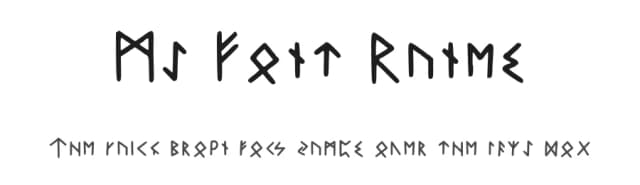
About My Font Runes Font
Lamentablemente no he podido diseñar el modelo de todos los iconstexts completos pero en lo personal diseñe los más usados o que considero son más prácticos, espero te guste el diseño ya que no fue robado, estudie el diseño de Runas Escandinavas y ese parece ser el modelo correcto del alfabeto en español para Latam-Espñ
My Font Runes Font
by Runas Escandinavas Diseño De Runas Real